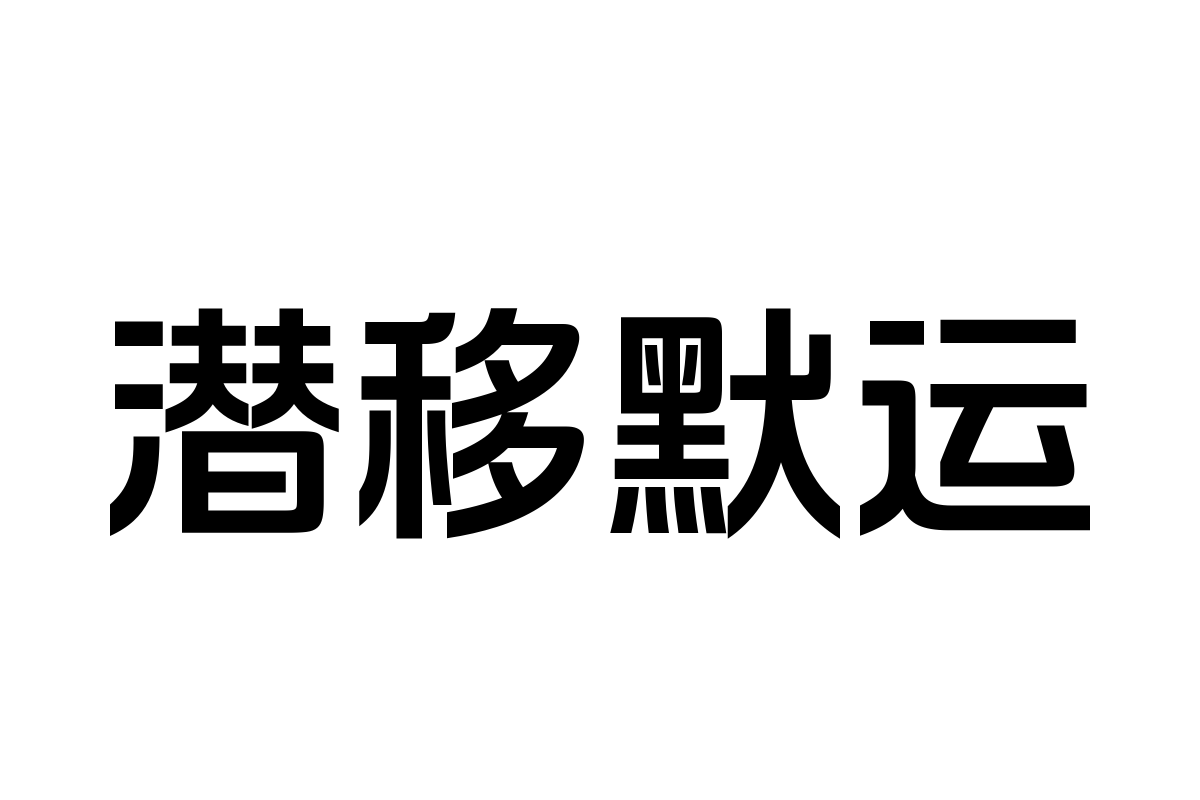
汉仪风尚黑65w是一款非常实用的字体,它拥有优雅的线条和独特的风格。这款字体适用于各种场合,包括广告、海报、书籍等。它的笔画流畅自然,给人一种舒适的感觉。
此外,汉仪风尚黑65w还具有很好的可读性,无论是在印刷还是电子屏幕上都能清晰显示。它的字体大小为65pt,非常适合用于标题和重要信息的文字展示。
总的来说,汉仪风尚黑65w是一款非常优秀的字体,无论是从美观度还是实用性方面都表现出色。